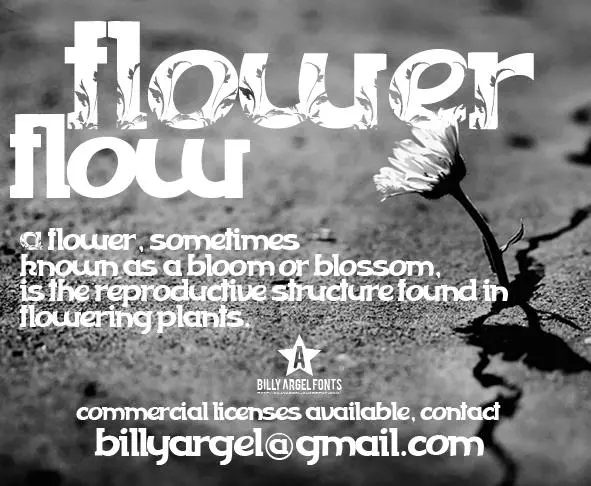
A FLOWERFLOW Font é uma fonte simbólica criada pelo designer Hamilton para aquelas criações digitais que precisam de uma identidade visual única e impactante. Essa fonte é perfeita para designers gráficos, ilustradores e quem está em busca de um tom distintivo em seus projetos. Com linhas elegantes e formas geométricas minimalistas, a FLOWERFLOW oferece um estilo moderno que se sobressai entre outras fontes. Ideal para identificar uma marca ou adicionar um toque especial aos elementos gráficos em sua produção, essa fonte não apenas dá o tom de seu design, mas também cria um impacto visual imediato e memorável. Se você busca incorporar um elemento distintivo que ressalte suas ideias, a FLOWERFLOW Font é uma escolha inteligente para qualquer projeto em sua carteira de trabalho. Visite BillyArgel.com ou entre em contato diretamente por email para mais detalhes.